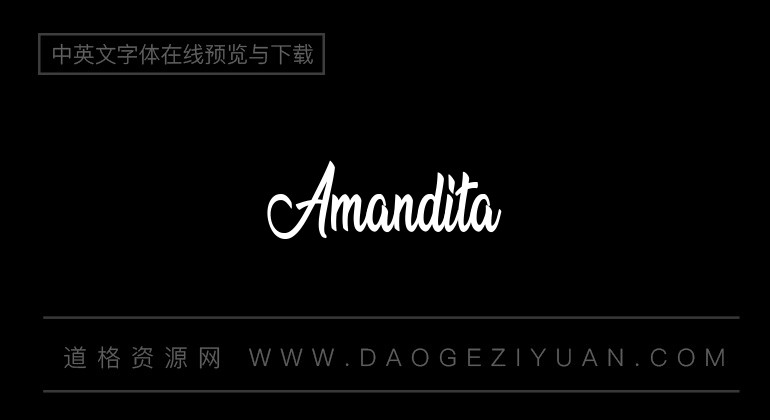
Amandita 是一款荷兰设计师Lida Lopes Cardozo 所设计的可爱活泼的手写体字体。它具有温柔而活泼的外观,可以帮助您创建有趣的设计,比如海报、书籍封面、标志和社交媒体图片等等。它的设计风格灵活多变,可以满足不同的设计需求,而且它的笔画细腻,可以为您的设计增添活力和活力。内容介绍
Amandita是一款非常不错的手写艺术字体,具有很好的视觉感,适合于文化类的宣传设计、商业类品牌的广告和产品包装设计以及个性化文字排版等较多场景。